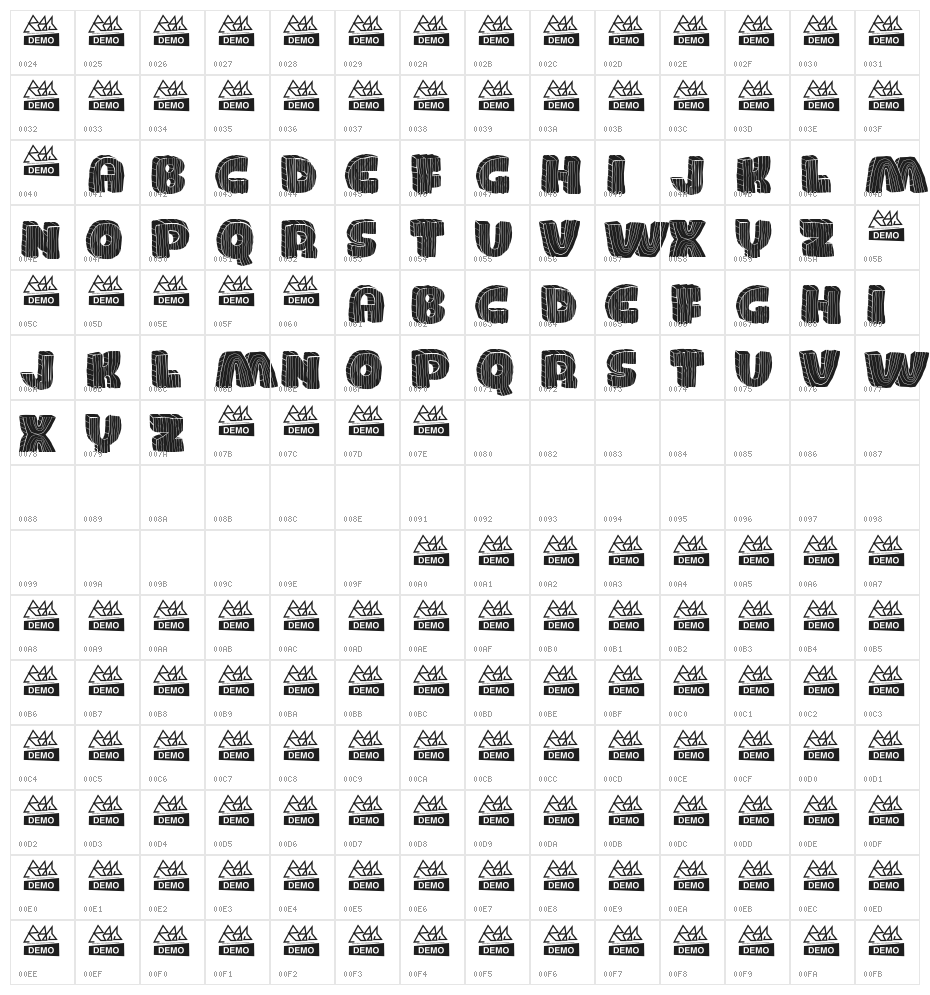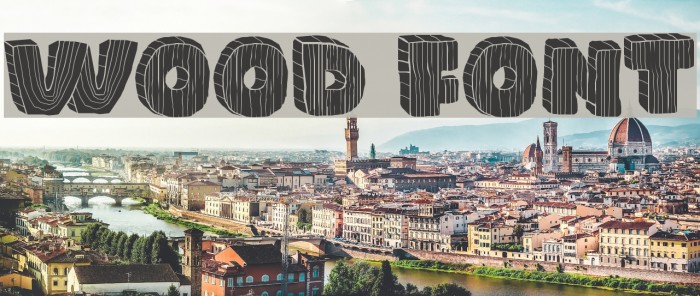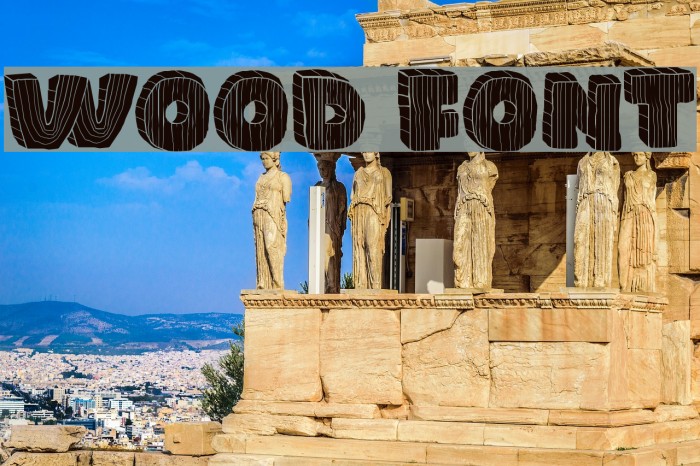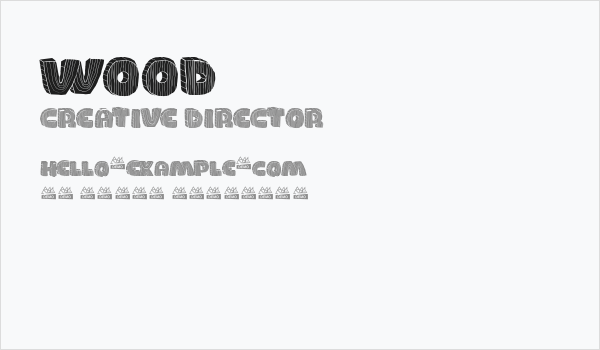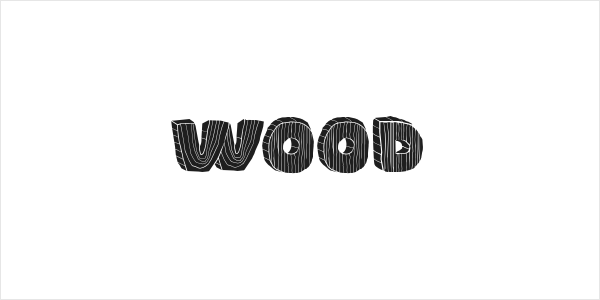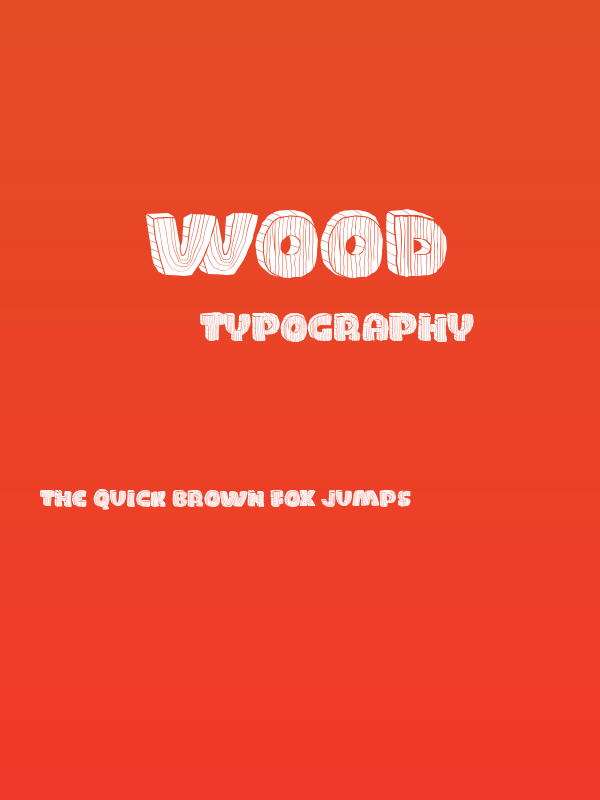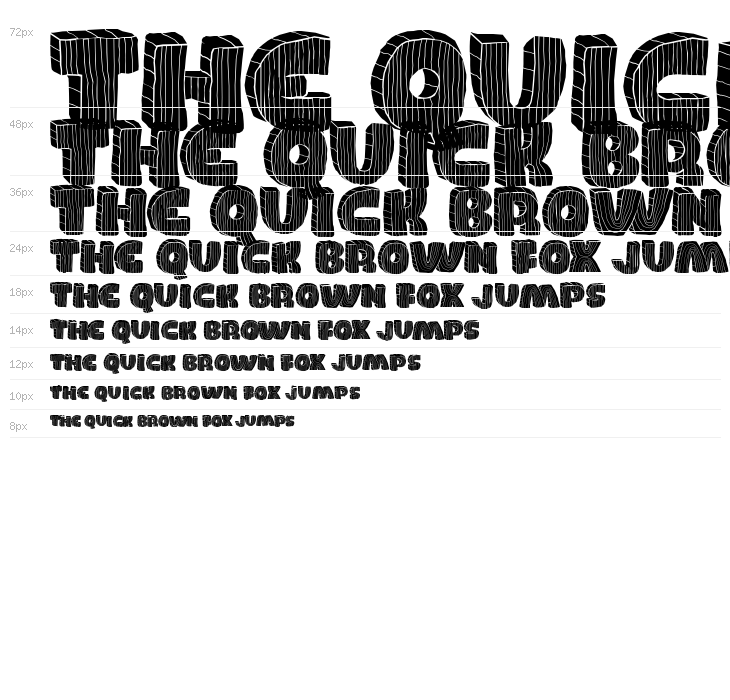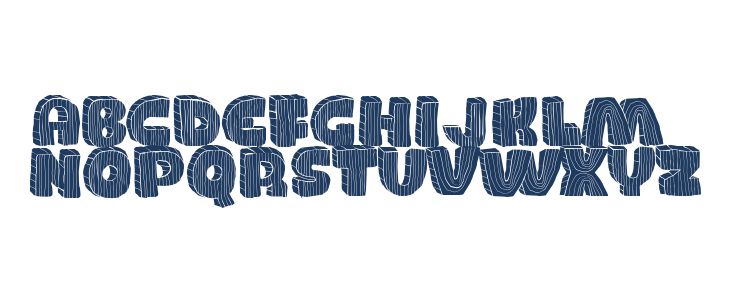
WOOD Font
Fonts by Rodrigo German - RASDESIGN
| Vorgeschlagene Projekte | Perfect for eco-friendly branding, nature-themed posters, rustic wedding invitations, and outdoor event signage. |